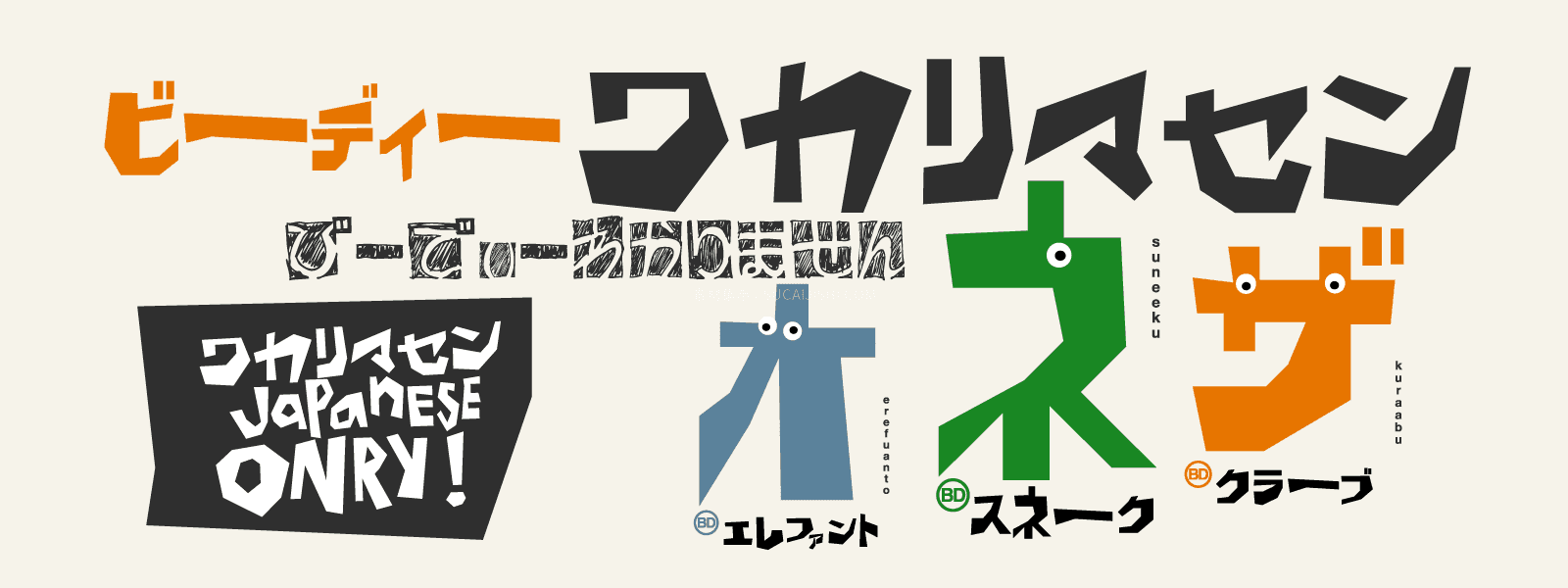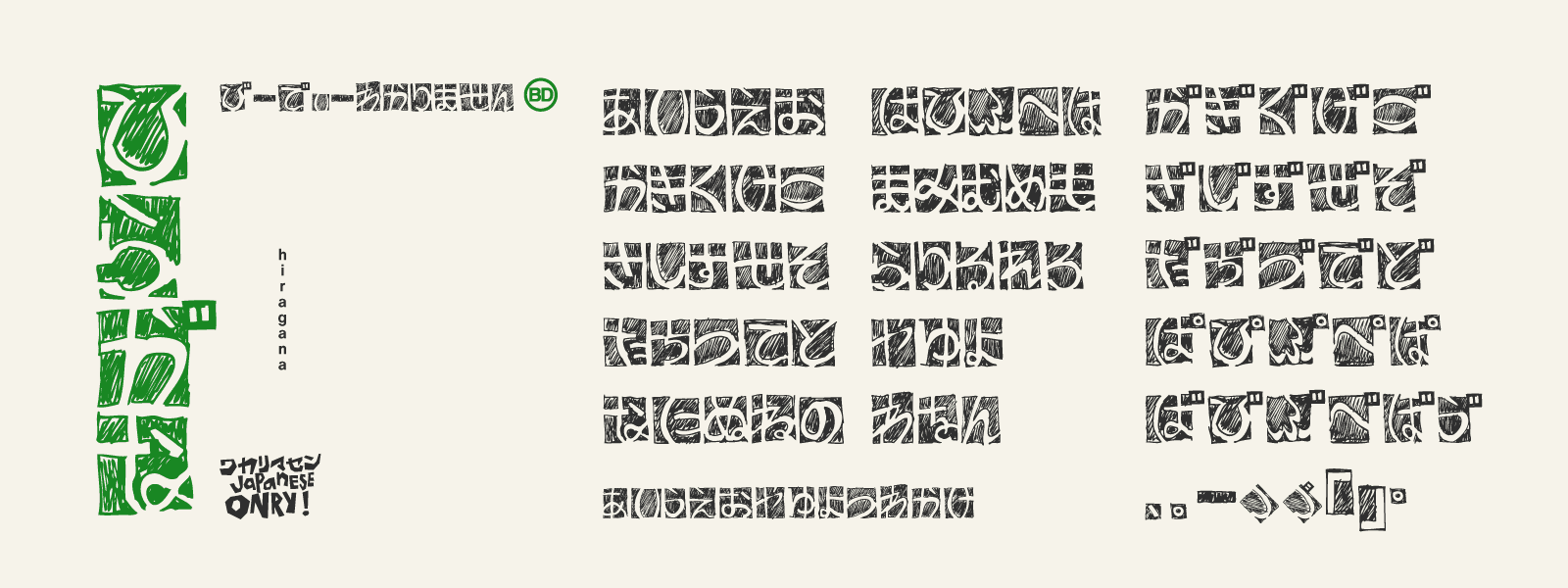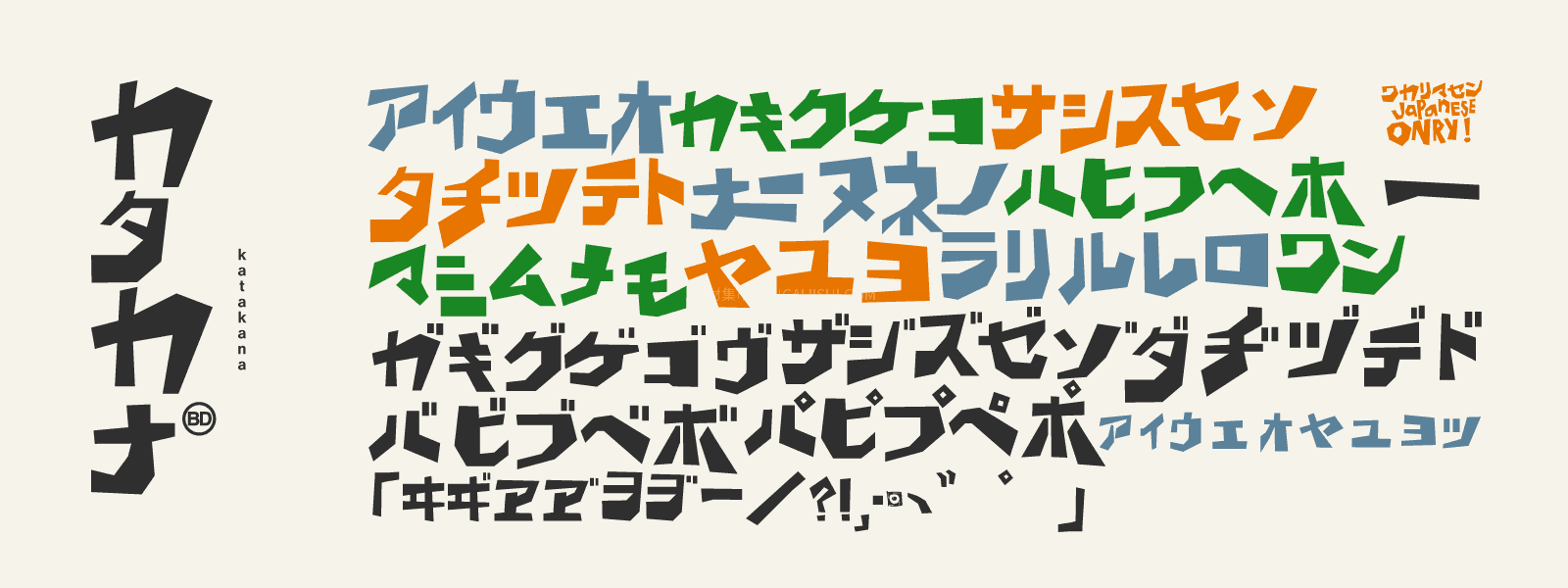
BD Wakarimasen 日系复古漫画风字体
这款超有个性的日式风格字体将平假名(原 BD Hiragana Kuro)与片假名(原 BD Wakarimasu)巧妙融合,混排时自带强烈的视觉张力和对比度!粗犷又活泼的字形加上锐利的棱角,瞬间拉满 80 年代复古街机游戏和热血漫画的氛围感,排版动感十足且充满趣味。(注意:这是一款纯假名字体,不包含任何拉丁字母哦!)